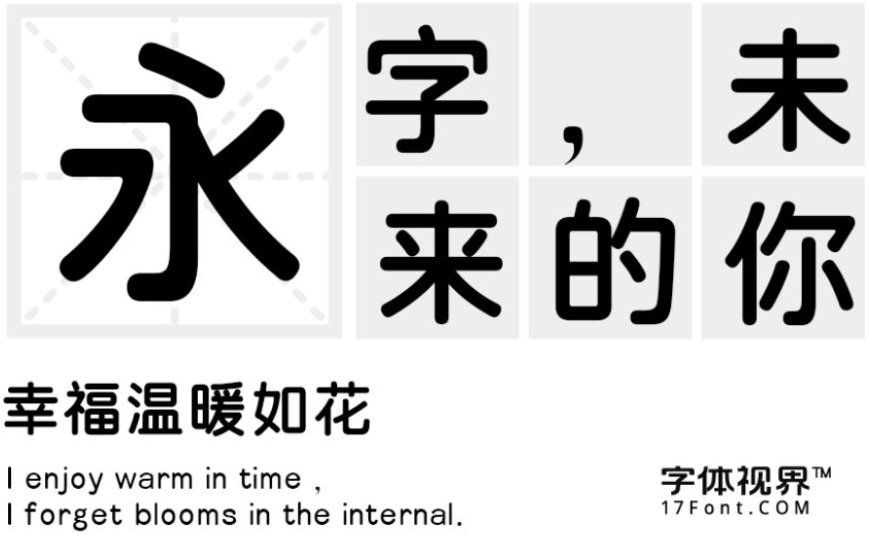
三极粗圆简体发布
字体名称:三极粗圆简体
字体类别: 书法字体、手写体
适用场景:广告、印刷、LOGO
三极粗圆简体简介:三极粗圆简体是一款稳重大气,极具观赏性的设计字体,字形稳重,结构严谨,字面较大。起笔收笔处为圆形,折笔圆弧,撇捺外延、增强了字体的识别性,字形更加圆润大气。适用于各类便携式屏幕的系统嵌入字体,以及传统印刷媒介的标题与正文排版。在品牌形象设计中作为logo设计性文字视觉效果更佳。
三极粗圆简体预览图展示: